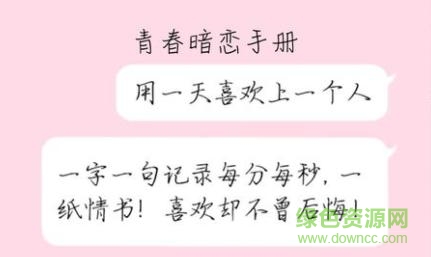
青春暗戀手冊(cè)ttf是一款小清新的手寫書法字體,這款字體給人的感覺就像是暗戀的感覺,非常要想表達(dá)自己但是又很含蓄,感興趣的朋友歡迎下載使用!
青春暗戀手冊(cè)ttf是一款提取自qq中的手寫字體,這款字體看上去非常的娟秀,并且連筆處理的非常漂亮,整體看上去會(huì)非常的賞心悅目!